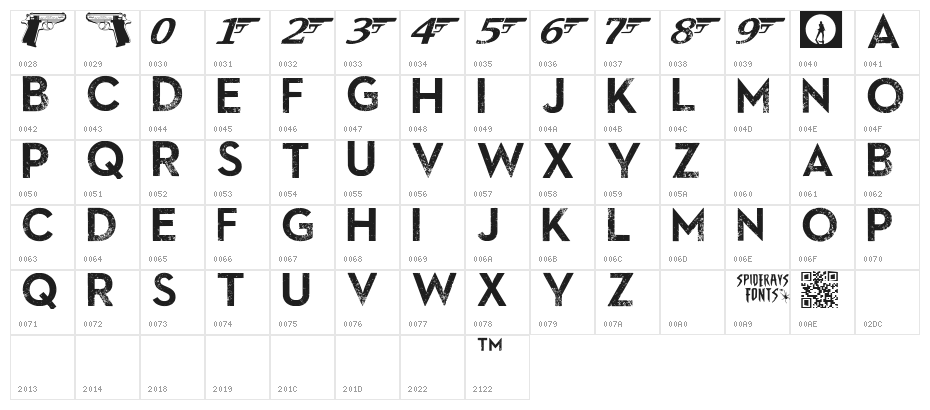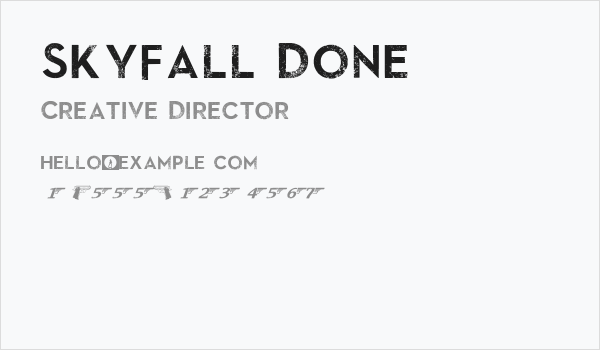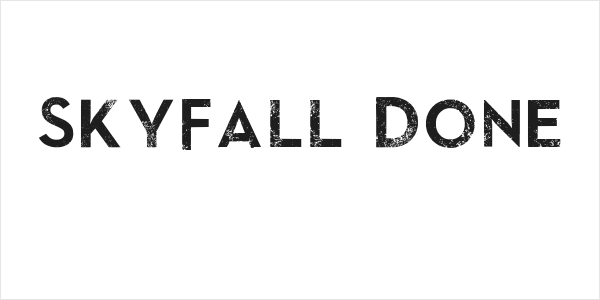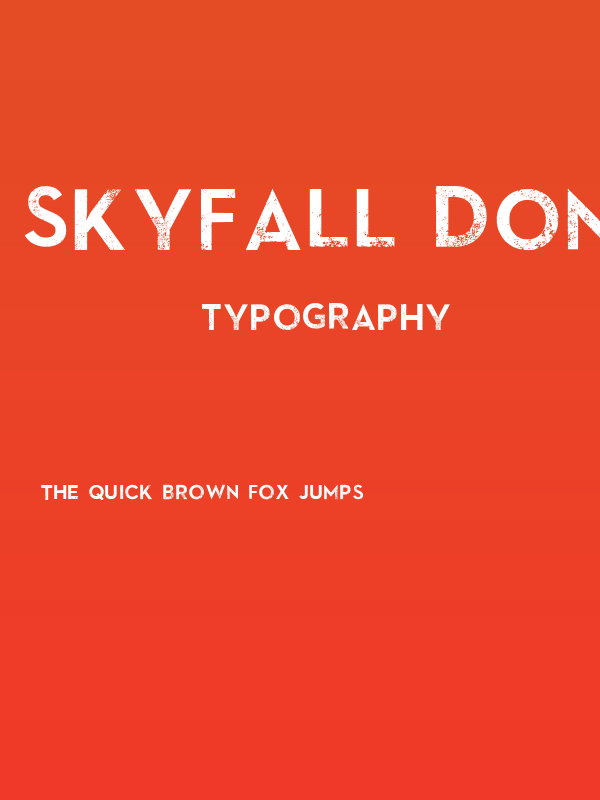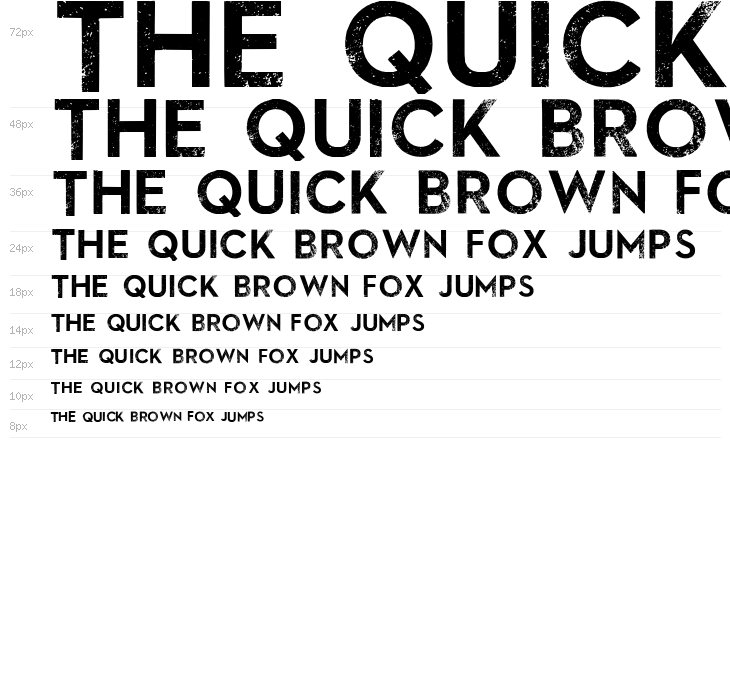
SkyFall Done Font
| Общий стиль | Vintage, Decorative |
| Рекомендуемые проекты | Ideal for movie posters, video game titles, action-themed branding, and promotional materials that require a bold, edgy look. |